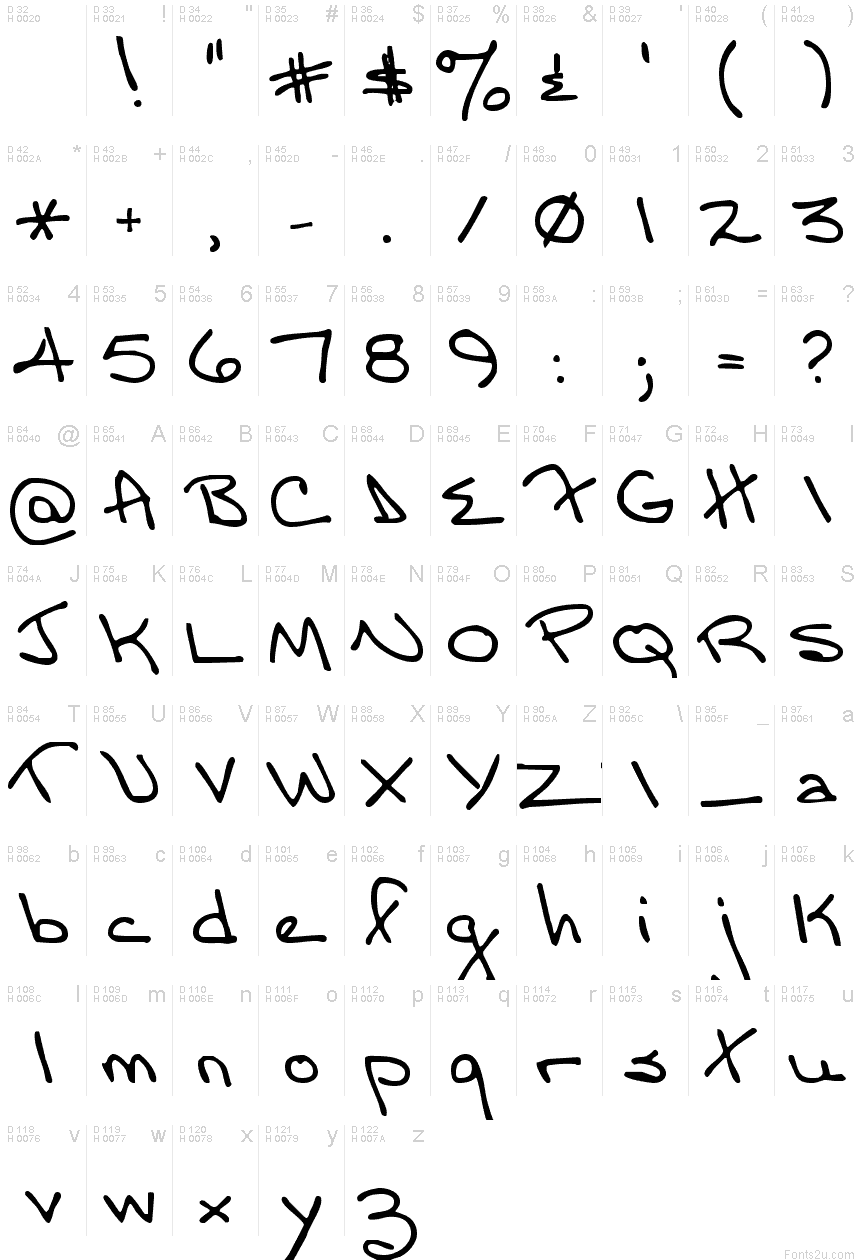
Moms Font od Ellinor je ručně psané písmo s uvolněným, osobním tahem a zaoblenými, mírně nepravidelnými znaky. Tvary si zachovávají nenucený, kreslený rytmus s měkkými křivkami a neformálním tokem, který působí spíše jako rychlá poznámka než uhlazený skript.
Moms Font se skvěle hodí na přáníčka, rodinné projekty, osobní branding, etikety na recepty, nadpisy do scrapbooků a grafiky s hřejivými citáty, protože dodává nezaměnitelný ručně psaný nádech, aniž by působil příliš upjatě. Hodí se také pro potřeby pro miminka, pozvánky a jednoduché příspěvky na sociální sítě, které vyžadují přátelský a domácí tón.